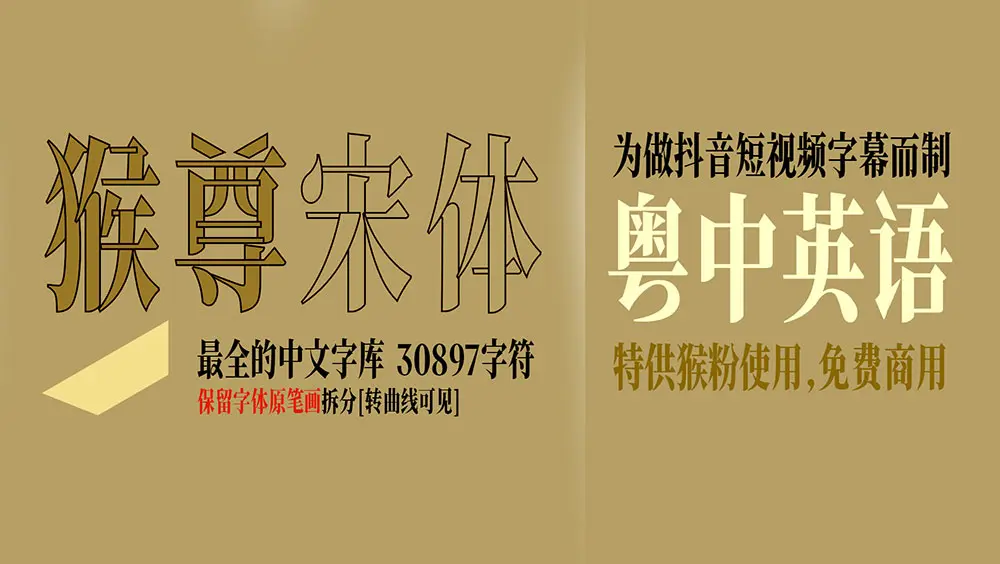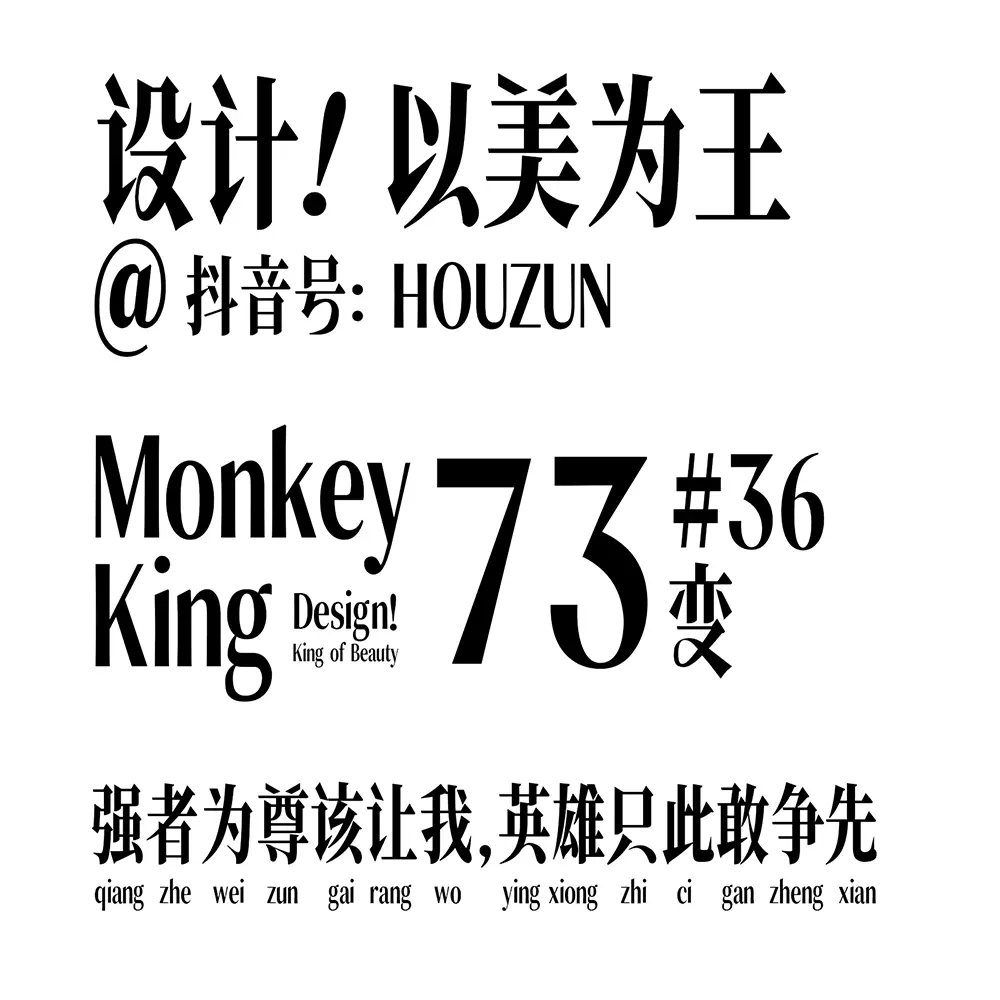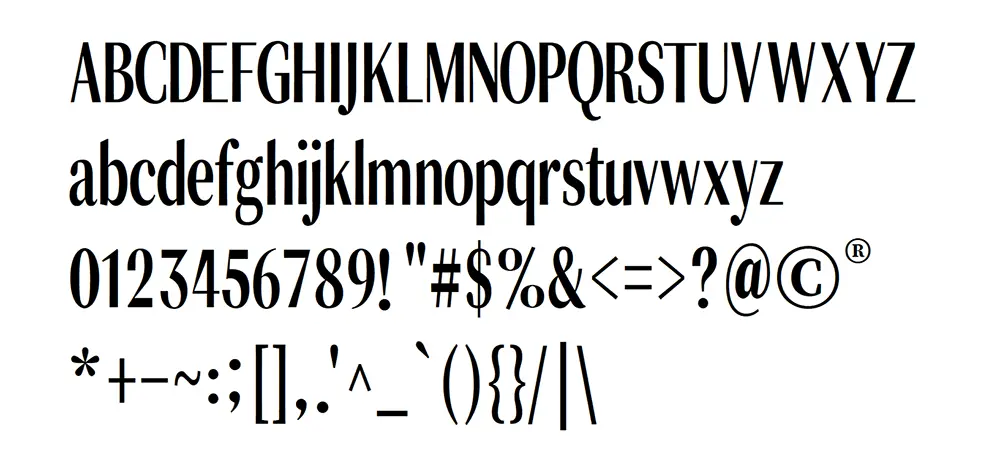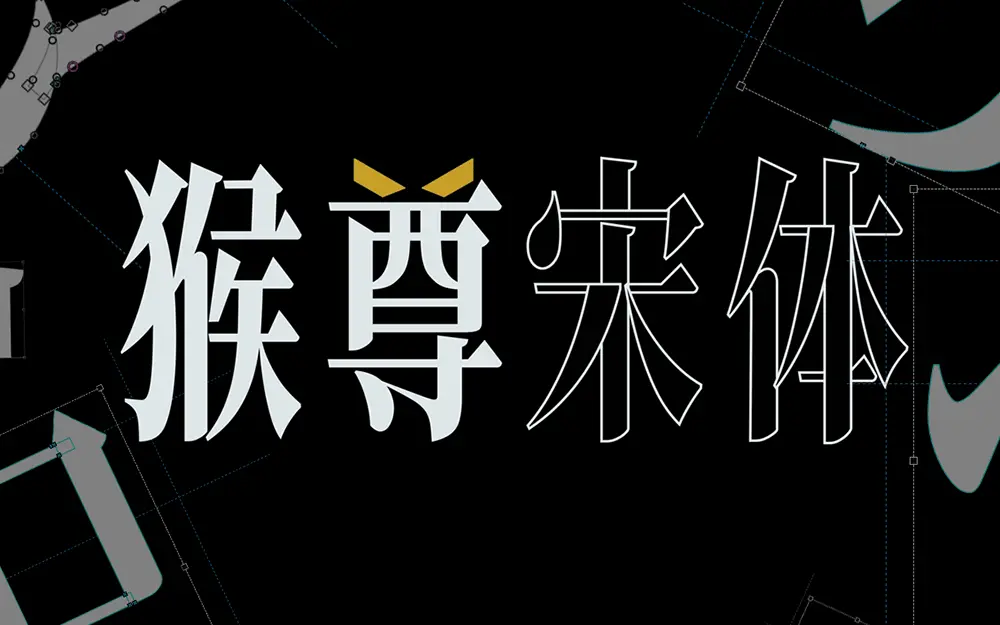
猴尊宋體預覽
猴尊宋體介紹
猴尊宋體是由抖音設計博主猴尊提供的一款免費商用字體,基於思源字體的比例更改為黃金比例值,部分字體筆畫、字母、數字、符號等字體重構設計,為短視頻的手機豎屏閱讀時,一行文字可放下更多(更大)的字,用於大標題時,依具精緻感。字體保留原筆畫不合並(轉曲線後可見,你可隨意繼續創新),個別筆畫加入書法手寫的筆畫感覺,字體有種獨特高雅的高級感!